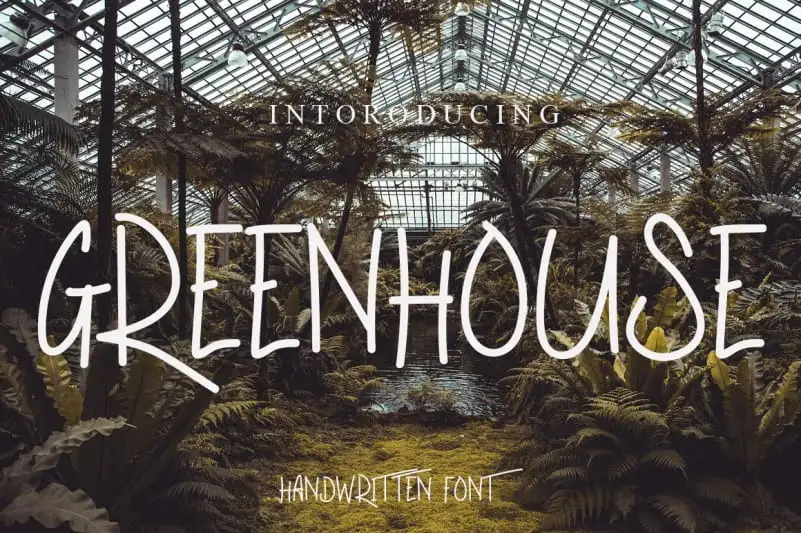
Greenhouse Display Font – Download Grátis
A ‘Greenhouse Display Font’ é uma fonte casual e natural para quem quer dar um toque especial a seu projeto digital. Inspirada no estilo das letras escritas à mão, essa fonte consegue transitar entre ser simples e ainda produzindo efeitos visuais fortes que destacam sua criação. Perfeita para trabalhos onde um ar de casualidade se mistura com um requinte natural, a ‘Greenhouse Display Font’ é uma escolha inteligente para aqueles que buscam transmitir personalidade ao mesmo tempo em que mantêm o foco no design legível e elegante. Sua versão display certamente fará sua criação destacar-se da multidão, tornando-a irresistivelmente atraente e original.